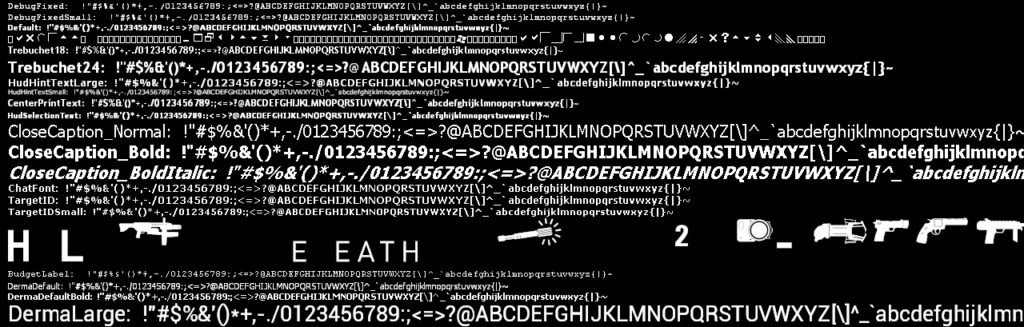
Garry's Mod es el paraíso de la personalización. Desde la creación de artilugios absurdos hasta el diseño de modos de juego completamente nuevos, la libertad es su pilar fundamental. Sin embargo, hay un aspecto de la personalización que a menudo se pasa por alto pero que tiene un impacto visual significativo: la tipografía. Las fuentes que vemos en el menú, en el chat o en el HUD (Heads-Up Display) definen en gran medida la atmósfera de nuestra experiencia. Muchos jugadores y desarrolladores de addons se preguntan cuál es la fuente oficial de Garry's Mod, cómo pueden cambiarla o si es posible añadir sus propias tipografías para darle un toque verdaderamente único a sus creaciones. En esta guía definitiva, resolveremos todas estas dudas, explorando desde la fuente inspirada en su icónico logo hasta el proceso técnico para implementar y utilizar fuentes personalizadas dentro del juego.
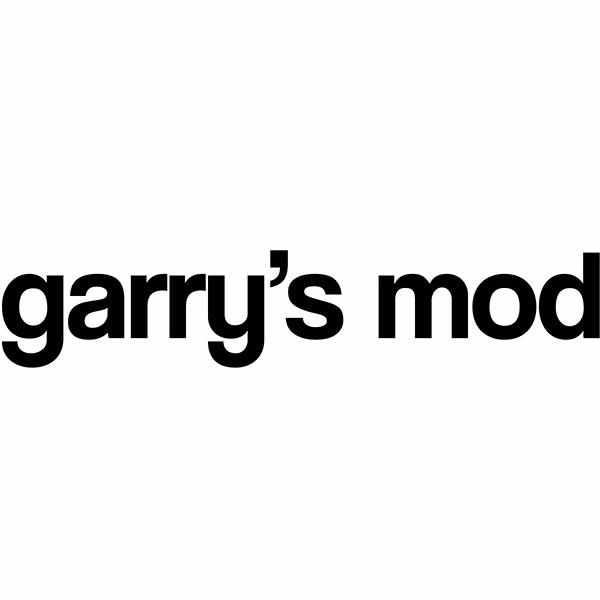
La Fuente Detrás del Logo: Coolvetica RG
Una de las preguntas más recurrentes es sobre la tipografía utilizada en el título del juego. Es importante aclarar que el juego en sí no utiliza una única fuente para todos sus textos, pero el logo tiene una estética muy particular que ha sido replicada. La fuente que captura a la perfección este estilo es Coolvetica RG, creada por Typodermic. Esta no es una fuente que venga con el juego, sino una tipografía basada en el diseño del logo, que a su vez se inspira en la clásica Helvetica con un toque más redondeado y amigable.
Coolvetica RG es una fuente gratuita, lo que la hace accesible para cualquier creador de contenido o jugador que desee emular la estética de Garry's Mod en sus propios proyectos, ya sean vídeos, miniaturas o interfaces personalizadas. Su diseño limpio y moderno la convierte en una opción versátil más allá del universo de GMOD. Es el ejemplo perfecto de cómo una comunidad puede tomar un elemento icónico de un juego y expandirlo, dándole vida propia fuera de su contexto original.
Un Vistazo a las Fuentes Predeterminadas de GMOD
Dentro del juego, la situación es muy diferente. No hay una sola fuente que lo domine todo. En su lugar, GMOD utiliza una amplia biblioteca de fuentes predefinidas, cada una asignada a diferentes elementos de la interfaz de usuario. Esto permite que el chat, la consola de desarrollador, los números del HUD y los menús tengan un aspecto distinto y funcionalmente apropiado.
Para los desarrolladores de addons y modos de juego, conocer estas fuentes es crucial. Utilizarlas asegura la consistencia con el juego base y garantiza que cualquier jugador pueda ver el texto correctamente sin necesidad de descargar archivos adicionales. Sin embargo, para proyectos que buscan una identidad visual única, estas fuentes pueden resultar limitantes. A continuación, presentamos una lista de algunas de las fuentes predeterminadas más comunes que encontrarás en Garry's Mod:
- Default Fonts: Default, DefaultBold, DefaultUnderline, DefaultSmall, DefaultLarge, DefaultFixed. Son las fuentes genéricas para la mayoría de los textos de la interfaz.
- HUD Fonts: HUDNumber, HUDNumber1 a 5, HudHintTextLarge, HudHintTextSmall. Específicamente diseñadas para los números y textos informativos del HUD, como la vida, la munición o las notificaciones.
- Menu & UI Fonts: MenuItem, TabLarge, UiBold, MenuLarge. Usadas en los menús principales y otras interfaces de usuario para garantizar la legibilidad.
- Chat & Console Fonts: ChatFont, ConsoleText. Optimizadas para el chat de texto y la consola de comandos, donde la claridad es esencial.
- Specific Game Fonts: HL2MPTypeDeath, TitleFont, TargetID. Heredadas de Half-Life 2 o diseñadas para propósitos muy específicos como los mensajes de muerte o el texto que identifica a un objetivo.
- Trebuchet Variants: Trebuchet18, Trebuchet19, Trebuchet20, Trebuchet22, Trebuchet24. Varias versiones de la popular fuente Trebuchet en diferentes tamaños, disponibles para uso general.
Esta variedad demuestra que los desarrolladores de Facepunch Studios pensaron en las diferentes necesidades de texto dentro del juego, pero también abrieron la puerta a que la comunidad fuera un paso más allá.
Guía para Crear y Usar Fuentes Personalizadas
Aquí es donde la verdadera magia comienza. Si las fuentes predeterminadas no son suficientes para tu visión creativa, Garry's Mod te permite crear y registrar tus propias fuentes a través de su API de scripting en LUA. Esto te da el poder de utilizar cualquier fuente que tengas instalada en tu sistema operativo o que incluyas en los archivos de tu addon.
Paso 1: La Función Clave `surface.CreateFont`
El corazón de la personalización de fuentes es la función surface.CreateFont. Esta función le dice al motor del juego que cree una nueva definición de fuente con parámetros específicos, a la que luego podrás llamar por un nombre único. La sintaxis básica es la siguiente:
surface.CreateFont( "NombreDeLaFuenteEnElPC", tamaño, peso, antialias, sombra, "NombrePersonalizadoEnElJuego" )
Vamos a desglosar el ejemplo proporcionado en la documentación de GMOD:
surface.CreateFont( "akbar", 48, 500, true, true, "MyFont" )
- "akbar": Es el nombre de la fuente que debe estar instalada en el sistema operativo del usuario (o incluida en tu addon). Puedes usar fuentes comunes como "Arial", "Verdana" o "Comic Sans MS".
- 48: Es el tamaño de la fuente en píxeles.
¿Qué es `color_white` en el ejemplo de código?
color_white es una variable global predefinida en el entorno LUA de Garry's Mod que representa el color blanco (RGB 255, 255, 255). Existen otras variables similares como `color_black`, `color_red`, etc. También puedes crear tus propios colores usando la estructura Color(r, g, b, a), donde r, g, b son los valores de rojo, verde y azul, y 'a' es la transparencia.